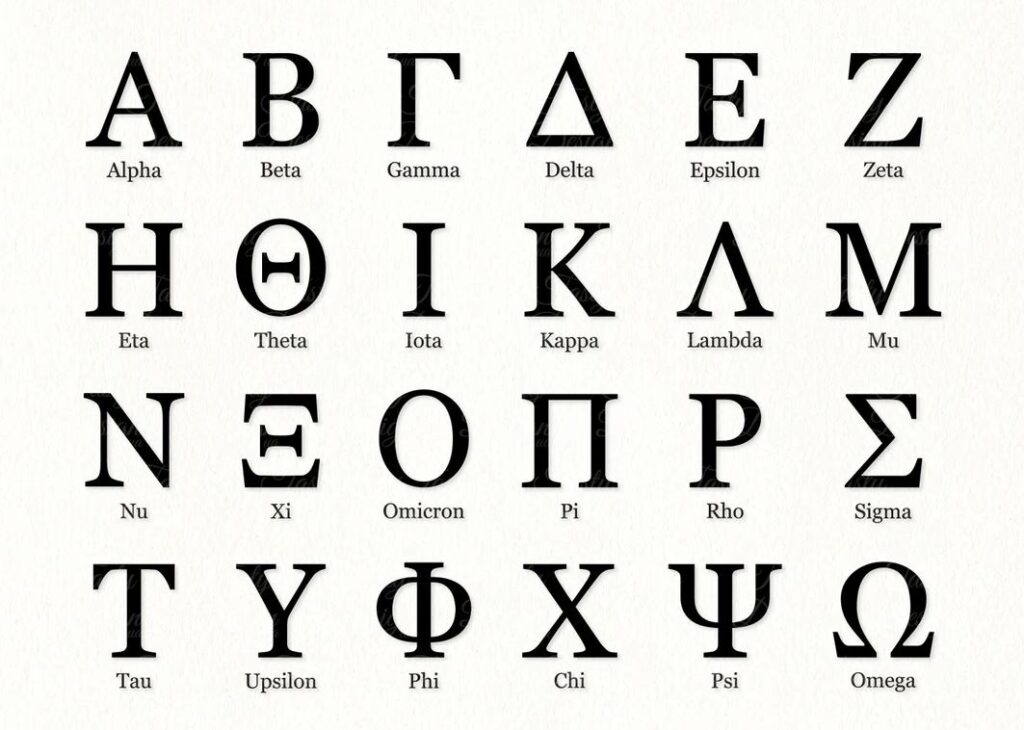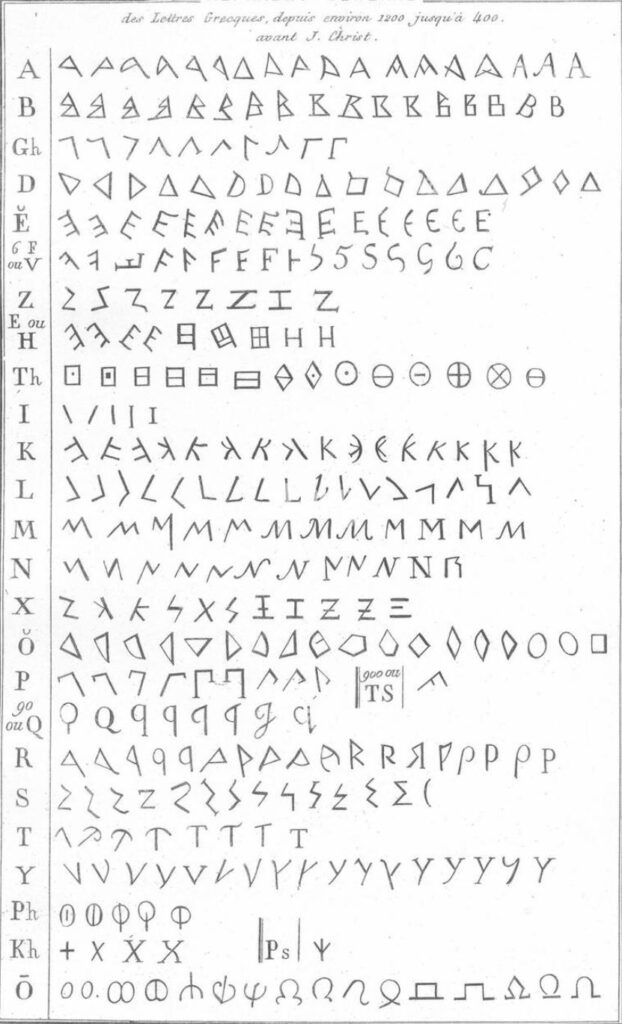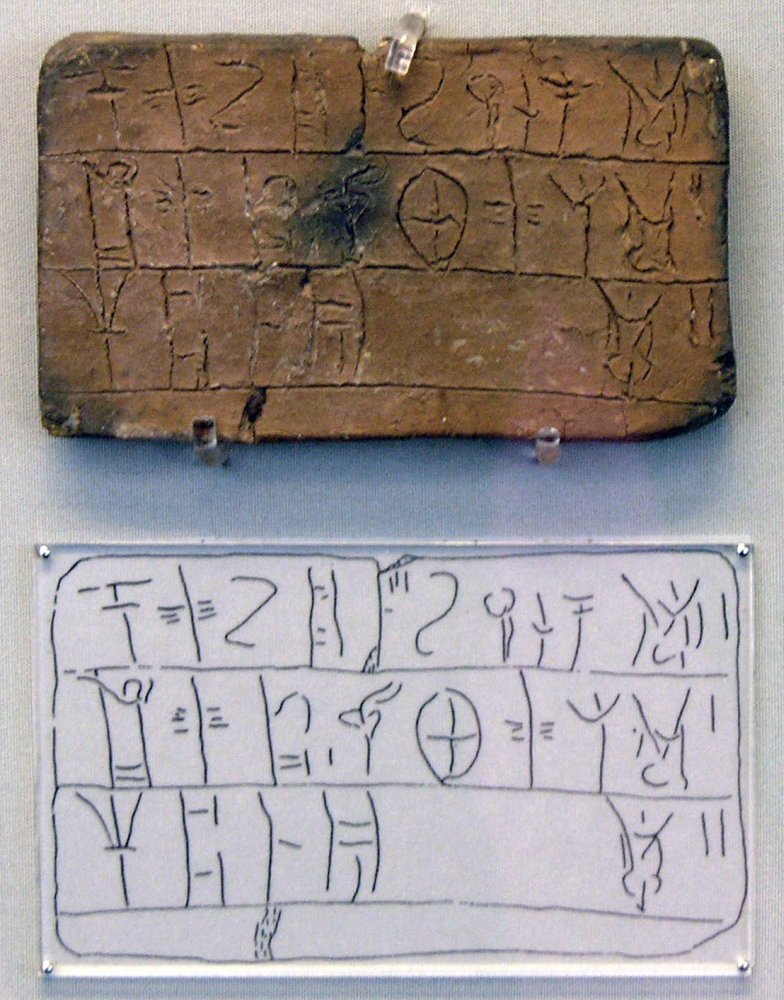
500 v. Chr.
im Grunde genommen geht das erste bekannte Alphabet der Griechen auf die kretisch-mykenische Silbenschrift Linear B zurück, die jedoch nur geringe Bedeutung hatte und bald wieder verschwand. Das klassische griechische Alphabet basiert hingegen auf den Buchstaben der Phönizier, mit denen die Griechen durch den Handel in Kontakt kamen. Die Griechen übernahmen das phönizische Alphabet und entwickelten es zu ihrer sogenannten Lapidarschrift weiter.
Da die griechische Sprache deutlich vokalreicher ist als die phönizische, fügten sie Vokale hinzu und änderten zugleich die Leserichtung. Bemerkenswerterweise spiegeln sich in der griechischen Schrift die geometrischen Grundformen der griechischen Architektur – Quadrat, Rechteck, Dreieck und Kreis – wider. Das griechische Alphabet gilt als Ursprung der späteren lateinischen Schrift.